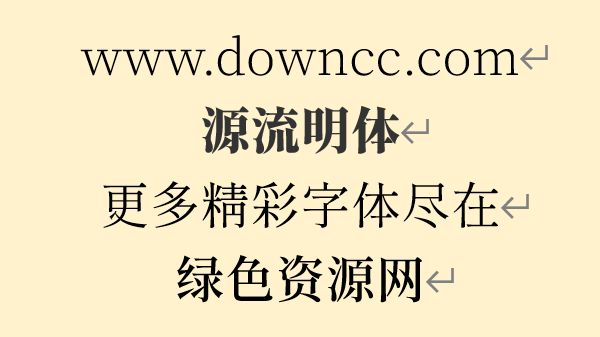
源流明體最新版為你提供了7個(gè)字重的字體,從最細(xì)到最粗一共7種。字體不錯(cuò),對(duì)于需要個(gè)性化的用戶來說是不錯(cuò)的。字體可以免費(fèi)商用,需要的朋友們歡迎下載!
源流明體是一款適用性非常廣泛的中文字體,該字體粗細(xì)適中,字形端正大方得體,包括了Bold、extralight、heavy、light、medium、regular、semibold等7種線條不一的字體
1、7個(gè)字重
完全重制思源宋體原來所有7個(gè)字重。 無論極粗或極細(xì),都能使用源流明朝的古典風(fēng)格!
3、漢字美感的改造
漢字寬度稍微壓縮,顯得比原始的思源宋體要稍微瘦長(zhǎng)。 并且在橫筆的起筆與豎筆的起筆、收筆處,全都加上粗細(xì)變化。 彷佛重現(xiàn)鉛字的壓印感,文字較有文學(xué)感、人文氣息。
Note. 請(qǐng)注意以上改造乃以電腦程式自動(dòng)進(jìn)行,未進(jìn)行任何人工處理,在部分筆畫復(fù)雜文字可能會(huì)有筆畫不太一致的情況。